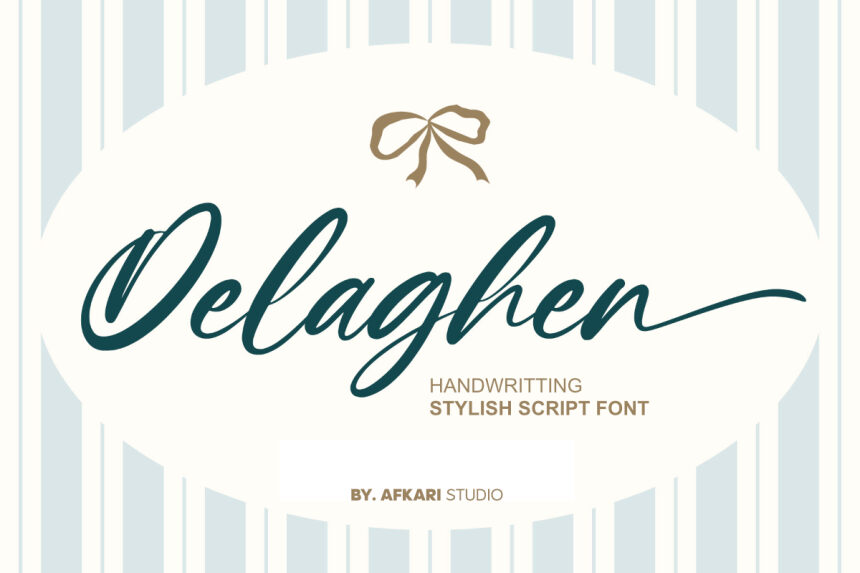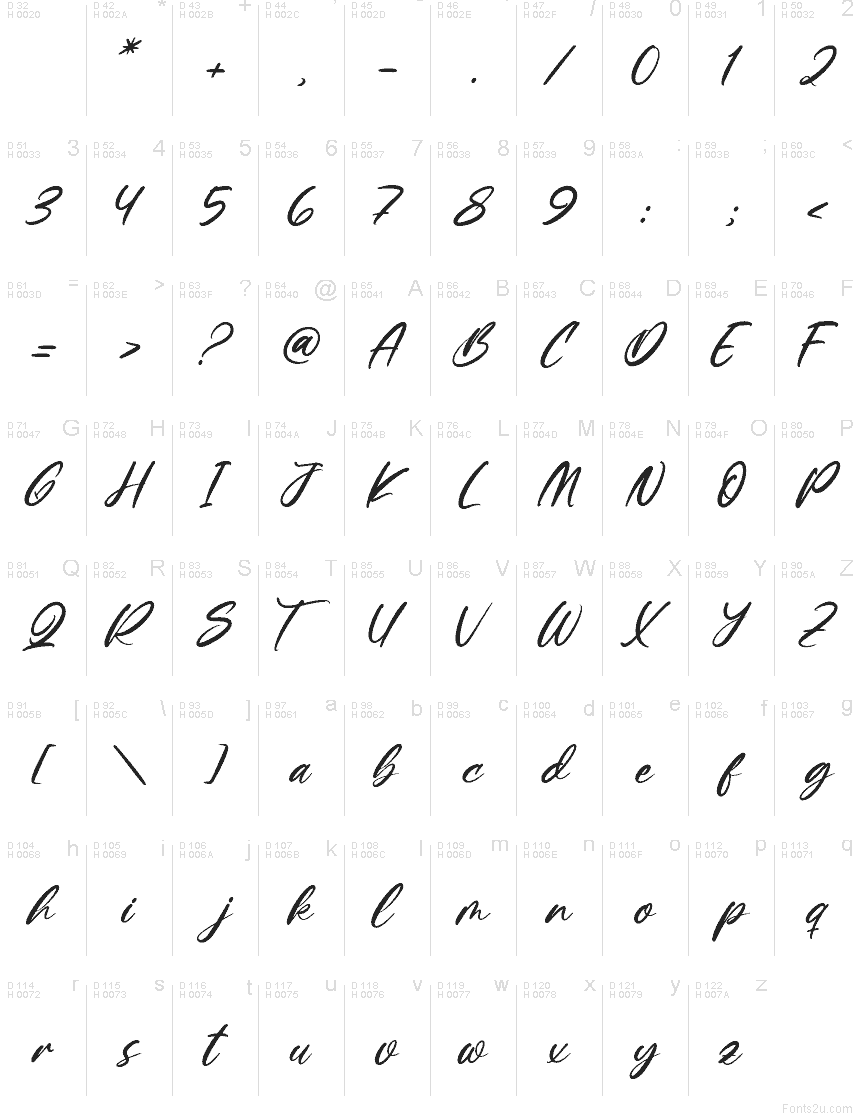
<p>Delaghen, da Afkari Studio, é uma fonte manuscrita gratuita com um estilo caligráfico fluido e traços longos e curvos. As letras conectam-se suavemente, com formas ovais altas e um toque dramático que confere ao design um ar elegante e autêntico, sem parecer rígido.</p>
<p>Adapta-se naturalmente a marcas de beleza, embalagens boutique, convites de casamento, lookbooks de moda e menus de café, onde uma fonte com tanto movimento pode definir o tom por conta própria. Use-a em títulos curtos, capas, logotipos ou monogramas, especialmente quando os traços estendidos de entrada e saída podem atravessar o layout e decorar o design para si.</p>